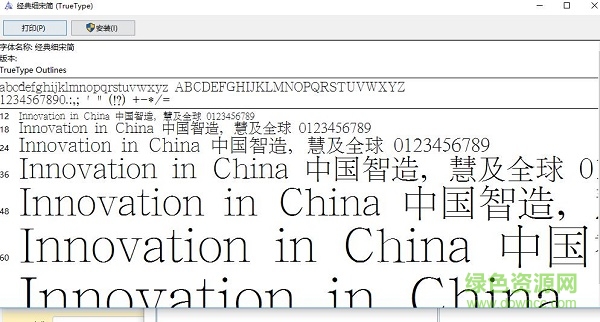
細(xì)宋體字體是一款比常規(guī)宋體要更細(xì)一些的中文常用字體,字體的線條干凈,骨絡(luò)分明,神采俊俏,廣告制作、印刷排版等各個(gè)領(lǐng)域皆可使用,需要的朋友趕緊下載吧!
【蒼勁古樸】
字體樸素?zé)o華,飽含古時(shí)之風(fēng)韻,能帶給人們一種懷舊感覺。
【穩(wěn)重挺拔】
字體造型規(guī)整,富于力度,給人以簡(jiǎn)潔爽朗的現(xiàn)代感,有較強(qiáng)的視覺沖擊力。
【活潑有趣】
字體造型生動(dòng)活潑,有鮮明的節(jié)奏韻律感,色彩豐富明快,給人以生機(jī)盎然的感受。